今回は「整」の書き方を解説します。
「整」の見本
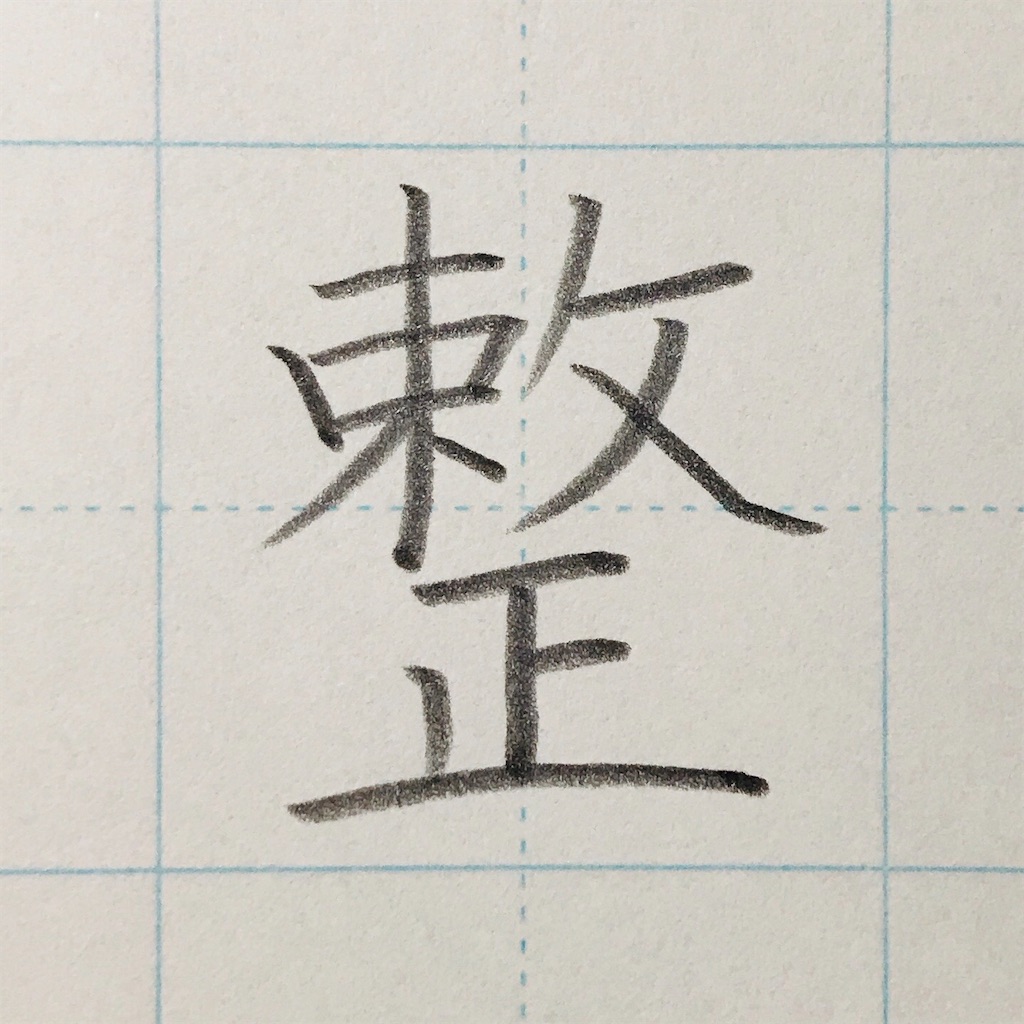
「整」の書き順
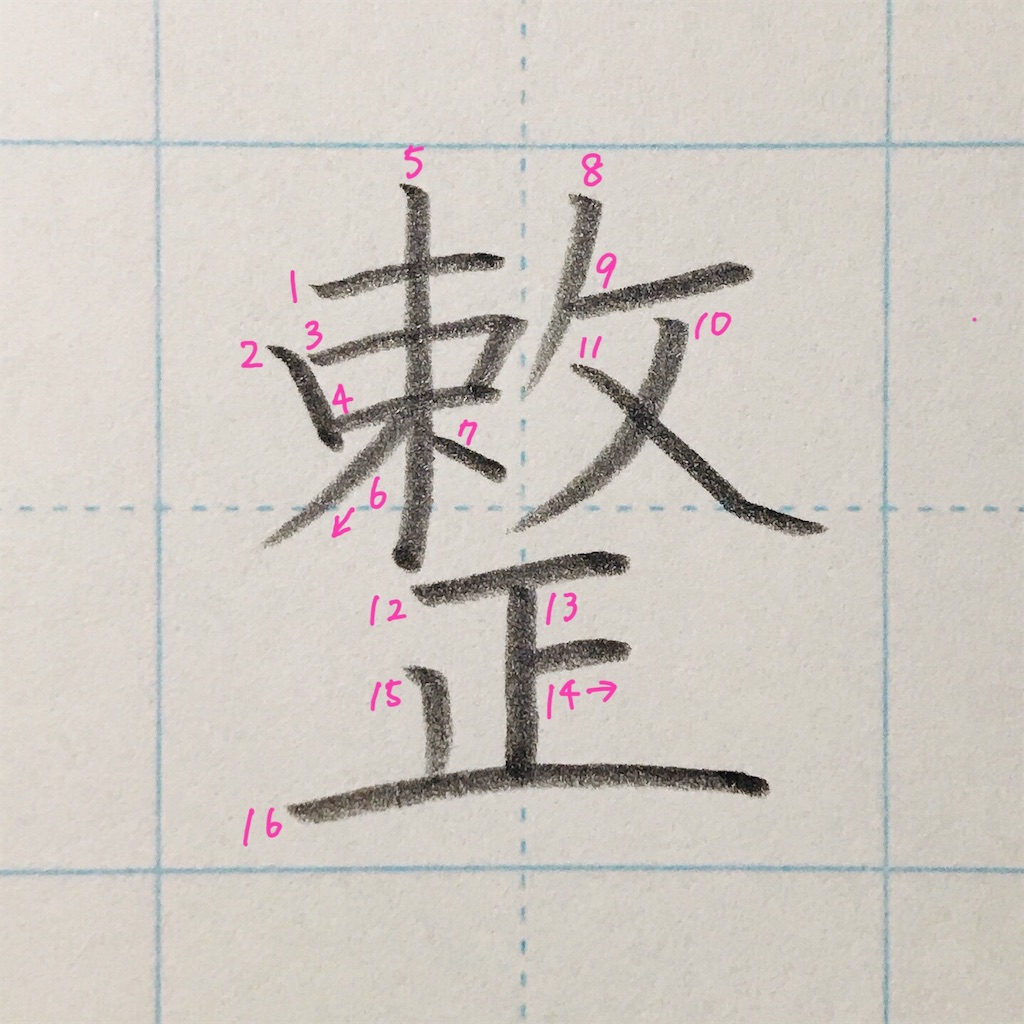
「整」の書き方ポイント
①右上がり、中心より少し左で止める。
②内に入れる。
③縦画と横画をそれぞれ出す。
④7画目のは少し下げる。ココは必ず空ける。
⑤均等に。
⑥縦に揃える。
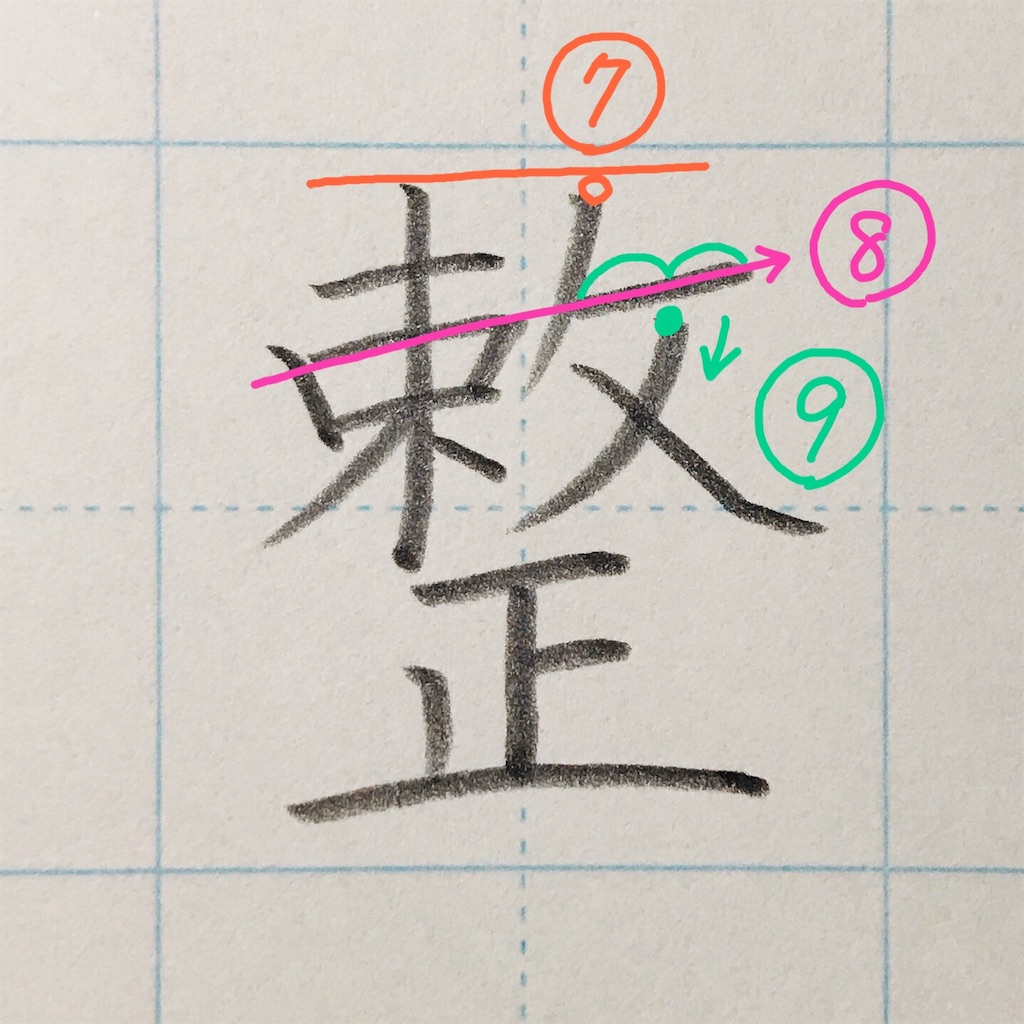
⑦少し下げる。
⑧3画目と9画目は、右上がりで一直線上に並ぶ。
⑨10画目は9画目の中心からスタートすると良い。
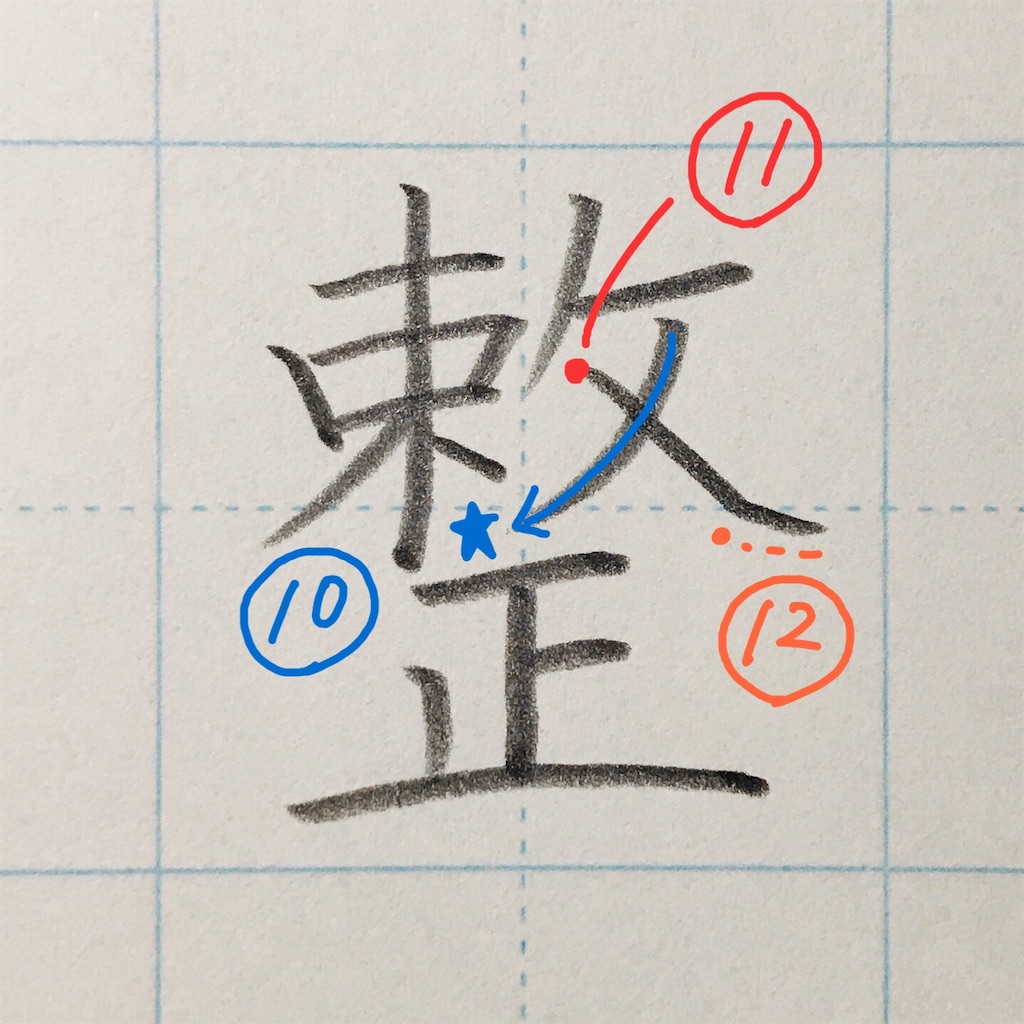
⑩★のスペースに向けて払うと◎。
⑪11画目は、8画目の払いの下の方からスタート。
⑫止めて、払う。
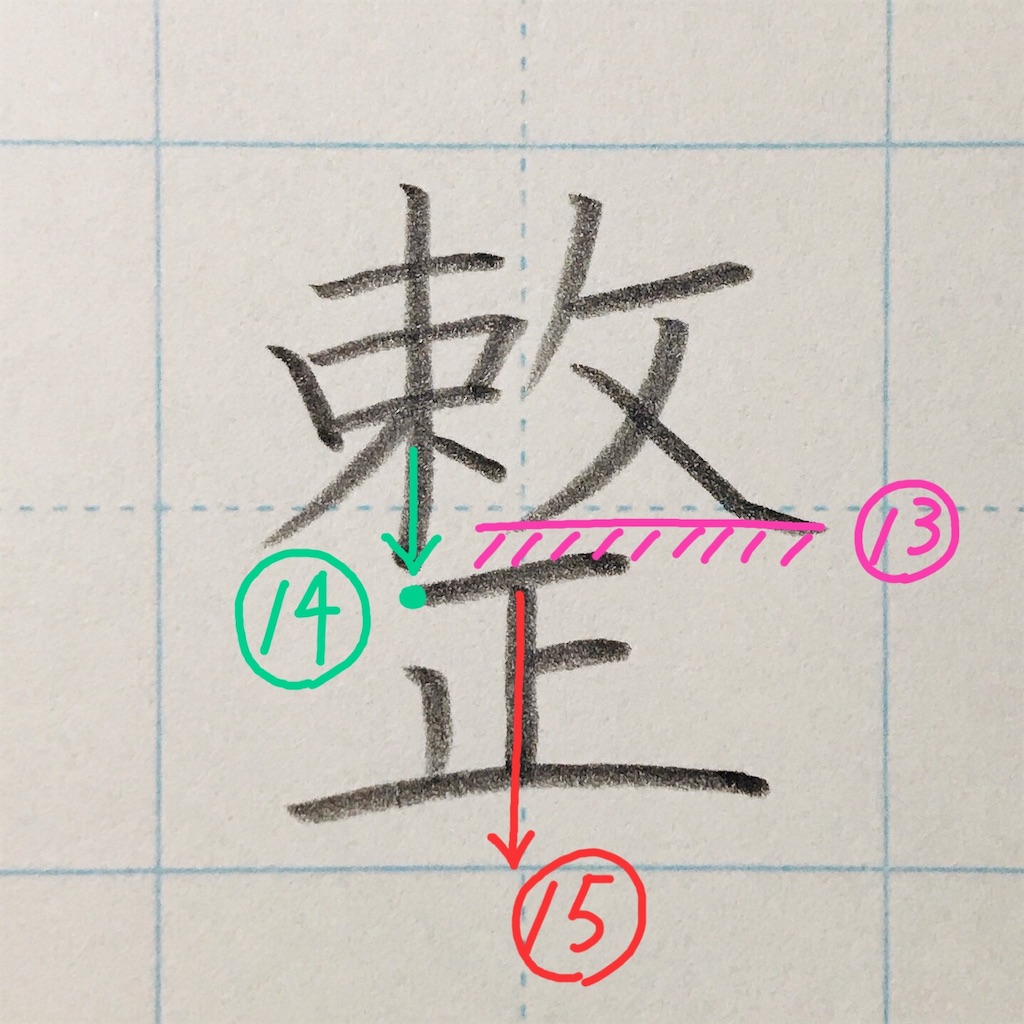
⑬余白を作る。
⑭「正」の1画目は5画目のすぐ下からスタート。
⑮中心に、まっすぐ。
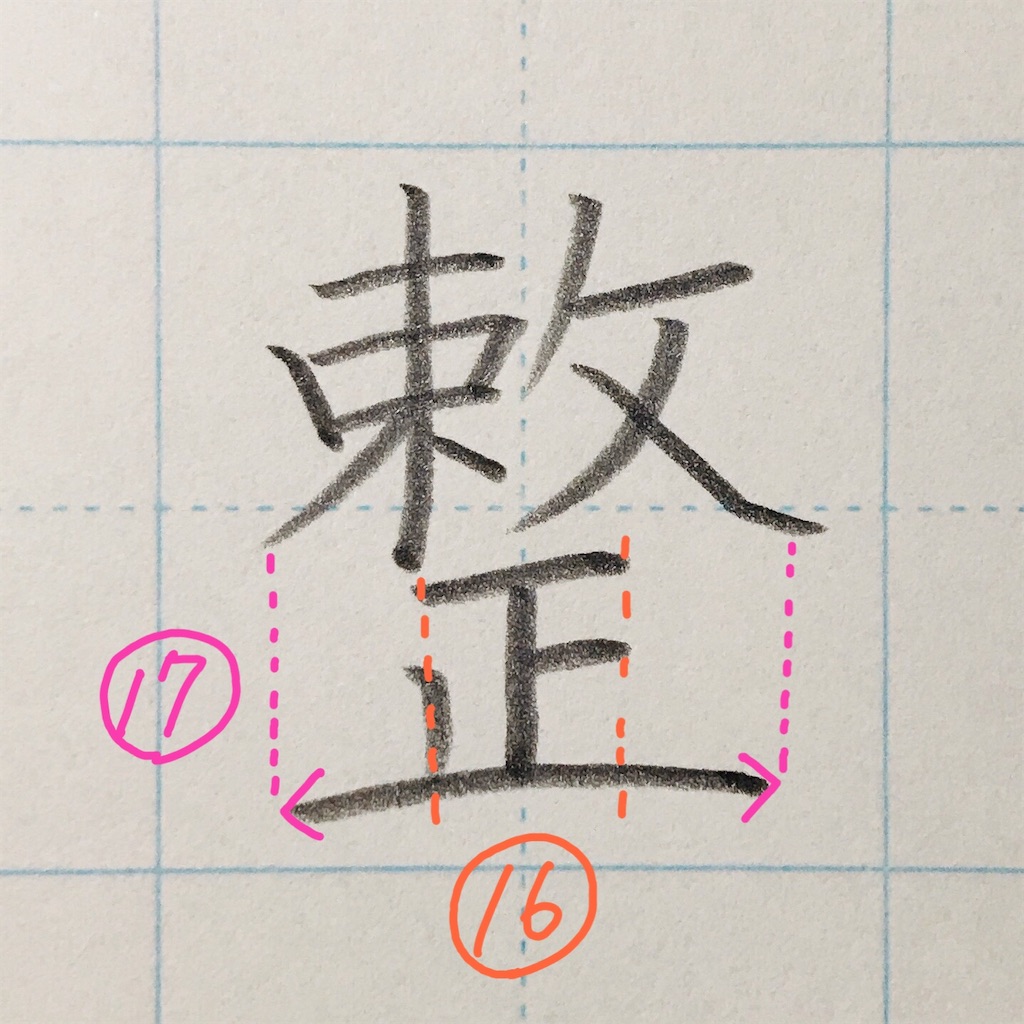
⑯幅を揃える。
⑰最終画は長く強調。
でも、左右はみ出さないように。
完成!